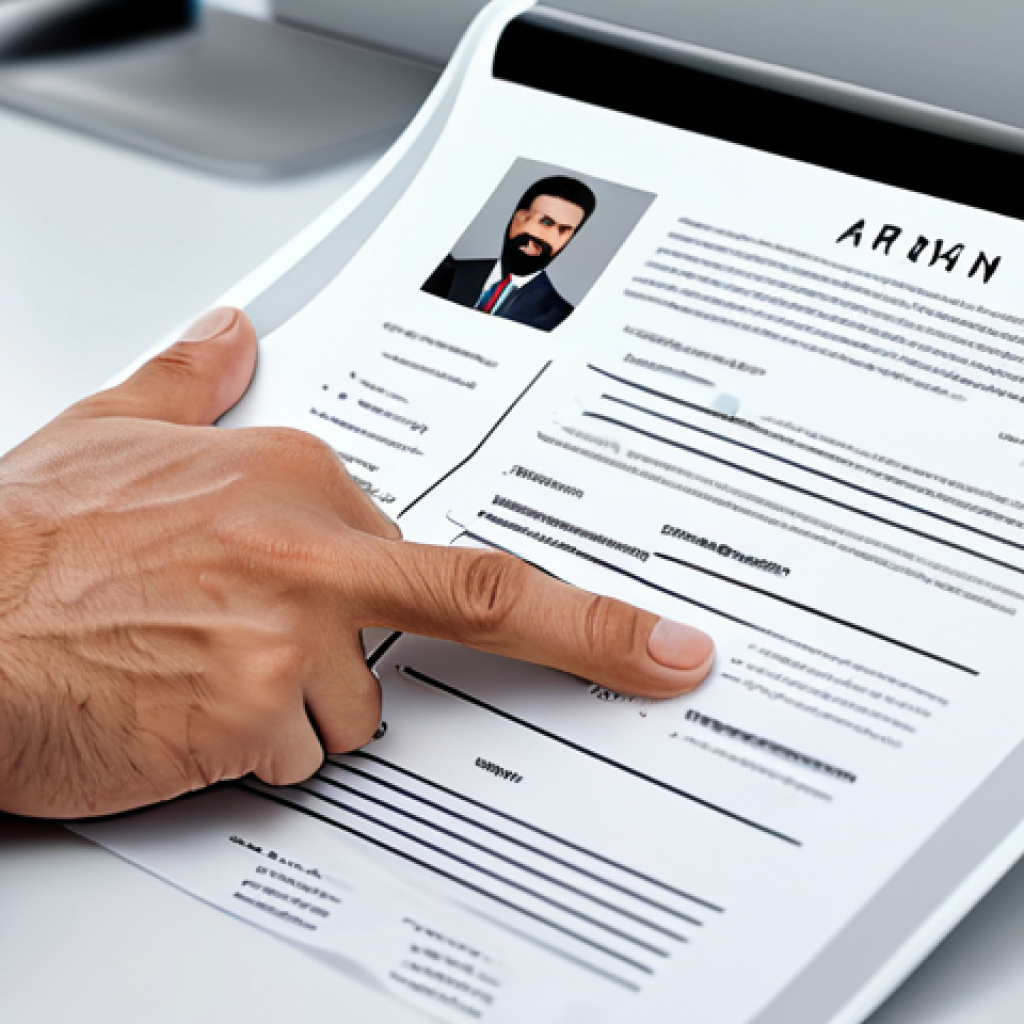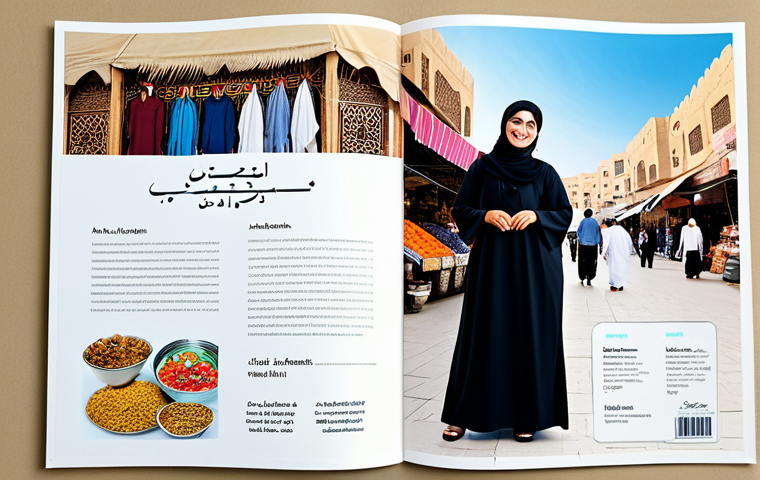
أسرار تنسيقات قوالب النصوص: خطوط تجذب القارئ وتوفر عليك الجهد.
الخطوط والأنماط المناسبة يمكن أن تحوّل مستنداتك من مجرد نصوص إلى أعمال فنية بصرية. فكر في الأمر، عندما تختار الخط المناسب، فإنك ترسل رسالة خفية حول شخصيتك أو هوية علامتك التجارية.
أنا شخصياً، أميل إلى استخدام خطوط بسيطة وأنيقة في رسائلي الرسمية، بينما أختار خطوطًا أكثر جرأة ومرحًا في تصميم الدعوات أو المواد الترويجية. تنسيق المستندات هو أكثر من مجرد اختيار الخطوط؛ يتعلق الأمر بخلق تجربة ممتعة للقارئ.
تصميم المستندات ليس مجرد مظهر، بل هو استثمار في انطباعك الأول. في عالم اليوم، حيث تتنافس المعلومات على جذب انتباهنا، يجب أن تكون مستنداتك جذابة بصريًا وسهلة القراءة.
أسلوب الخط ولونه وحجمه، كلها عوامل تؤثر في كيفية استقبال رسالتك. تذكر دائمًا، البساطة هي المفتاح. تجنب الفوضى البصرية واستخدم المساحات البيضاء بحكمة لإبراز المحتوى الأساسي.
هذا الأمر ليس مجرد رأي شخصي، بل هو اتجاه متزايد في عالم التصميم، حيث يفضل الناس تجارب بسيطة وسلسة. فكر في كيف تغيرت مواقع الويب والتطبيقات على مر السنين، كلها تسعى إلى تصميم أكثر نظافة وأقل تعقيدًا.
أفضل قوالب المستندات والخطوط الأنيقة لعام 2024* قوالب الأعمال: إذا كنت تبحث عن قالب رسمي واحترافي، فابحث عن قوالب ذات تصميم بسيط وأنيق. خطوط مثل “Roboto” و “Open Sans” هي خيارات ممتازة.
هذه الخطوط سهلة القراءة وتضفي مظهرًا عصريًا على مستنداتك. * قوالب التسويق: لإعلاناتك ومنشوراتك على وسائل التواصل الاجتماعي، جرب قوالب أكثر جرأة وإبداعًا.
خطوط مثل “Montserrat” و “Playfair Display” يمكن أن تجذب الانتباه وتساعد في إيصال رسالتك بفعالية. * قوالب شخصية: لرسائل البريد الإلكتروني والدعوات، اختر قوالب تعكس شخصيتك.
خطوط مثل “Lato” و “Merriweather” هي خيارات رائعة تجمع بين الأناقة والود. نصائح لتحسين قراءة المستندات:* التناسق: استخدم نفس الخط والنمط في جميع أنحاء المستند.
هذا يمنح المستند مظهرًا موحدًا واحترافيًا. * التباين: تأكد من وجود تباين كافٍ بين لون الخط ولون الخلفية. هذا يجعل النص سهل القراءة.
* الحجم: اختر حجم خط مناسبًا. حجم الخط القياسي هو 12 نقطة، لكن قد تحتاج إلى زيادة الحجم إذا كان جمهورك المستهدف من كبار السن أو الأشخاص ذوي الإعاقة البصرية.
* المسافات: استخدم مسافات مناسبة بين الأسطر والفقرات. هذا يجعل النص أسهل في القراءة ويمنح القارئ فرصة لأخذ استراحة بصرية. مع التطور السريع للتكنولوجيا، من المتوقع أن نشهد المزيد من التوجه نحو استخدام الذكاء الاصطناعي في تصميم المستندات.
قد نرى أدوات تستخدم الذكاء الاصطناعي لتحليل محتوى المستند واقتراح أفضل الخطوط والأنماط تلقائيًا. هذا يمكن أن يوفر الكثير من الوقت والجهد للمستخدمين، خاصة أولئك الذين ليس لديهم خبرة في التصميم.
أيضاً، نتوقع أن نرى المزيد من التركيز على إمكانية الوصول في تصميم المستندات. يجب أن تكون المستندات متاحة لجميع الأشخاص، بغض النظر عن قدراتهم. هذا يعني استخدام خطوط سهلة القراءة، وألوان ذات تباين عالٍ، وتوفير بدائل نصية للصور.
لنجعل مستنداتك متميزة وجذابة، لنتعرف على ذلك بدقة!
أهمية اختيار الخط المناسب في تصميم المستندات
تأثير الخط على الانطباع الأول
اختيار الخط المناسب ليس مجرد تفصيل تقني، بل هو عنصر أساسي يؤثر بشكل كبير على الانطباع الأول الذي يتركه المستند على القارئ. تخيل أنك تلقيت سيرة ذاتية مكتوبة بخط غير احترافي أو صعب القراءة؛ غالباً ما يكون رد فعلك الأولي هو التقليل من جدية صاحب الطلب.
الخط الواضح والأنيق يعكس الاحترافية والاهتمام بالتفاصيل، بينما الخط الفوضوي أو غير المناسب يمكن أن يوحي بالإهمال وعدم المبالاة. من تجربتي الشخصية، عندما كنت أبحث عن متدربين في شركتي، كنت أميل إلى تجاهل السير الذاتية التي تستخدم خطوطًا غير تقليدية أو مزعجة للعين، لأنها تعكس صورة غير موثوقة عن المرشح.
الأمر لا يقتصر فقط على المظهر، بل يتعلق أيضاً بكيفية معالجة المعلومات؛ الخط الجيد يسهل على القارئ فهم المحتوى ويجعله أكثر متعة للقراءة.
كيف يعكس الخط هوية العلامة التجارية
الخط الذي تستخدمه في مستنداتك ليس مجرد أداة للتعبير عن الكلمات، بل هو جزء لا يتجزأ من هوية علامتك التجارية. فكر في شعار شركة “كوكاكولا” الشهير، الخط المميز المستخدم فيه أصبح مرادفاً للعلامة التجارية نفسها.
الخطوط لها شخصيات مختلفة؛ بعضها رسمي وجاد، والبعض الآخر مرح وعصري. اختيار الخط المناسب يساعد في توصيل القيم والمبادئ التي تمثلها علامتك التجارية. على سبيل المثال، إذا كانت شركتك تقدم خدمات مالية، فإن استخدام خط كلاسيكي مثل “Times New Roman” يمكن أن يعزز الثقة والمصداقية.
بالمقابل، إذا كانت شركتك تعمل في مجال التصميم أو الإبداع، فإن اختيار خط مبتكر وجريء يمكن أن يعكس الإبداع والابتكار. من خلال تجربتي في العمل مع شركات ناشئة، لاحظت أن الشركات التي تستثمر في تصميم علامتها التجارية بشكل متكامل، بما في ذلك اختيار الخط المناسب، تحقق نتائج أفضل على المدى الطويل.
أفضل الممارسات لتنسيق المستندات بشكل فعال
أيضاً، تأكد من أن المستند متوافق مع برامج قراءة الشاشة للأشخاص ذوي الإعاقة البصرية.
س: ما هي الاتجاهات المستقبلية في تصميم المستندات؟
ج: نتوقع رؤية المزيد من استخدام الذكاء الاصطناعي في تصميم المستندات، حيث ستساعد الأدوات الذكية في تحليل المحتوى واقتراح أفضل الخطوط والأنماط تلقائيًا. بالإضافة إلى ذلك، سيكون هناك تركيز أكبر على إمكانية الوصول، مما يعني تصميم مستندات متاحة لجميع الأشخاص، بغض النظر عن قدراتهم، من خلال استخدام خطوط سهلة القراءة، وألوان ذات تباين عالٍ، وتوفير بدائل نصية للصور.